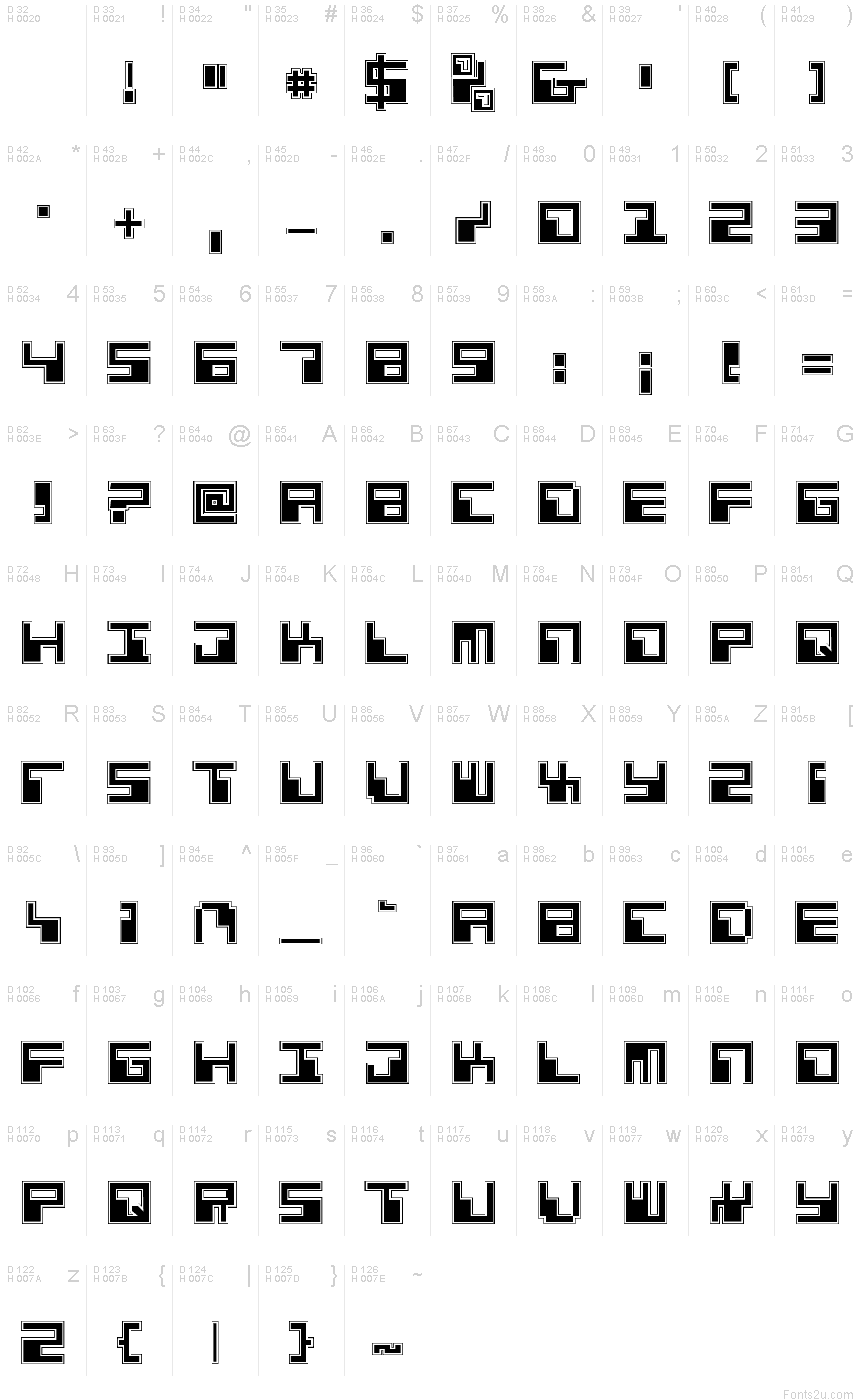
Phaser Bank Pro od Iconian Fonts to darmowy, futurystyczny font typu display w stylu techno, z szerokimi, kwadratowymi wielkimi literami i wyrazistą konstrukcją dwuliniową. Litery kojarzą się ze znakami sci-fi z automatów do gier lub paneli sterowania, z pudełkowymi kształtami zewnętrznymi, wpuszczanymi obrysami i prostymi kątami, które powtarzają się w całym kroju.
Naturalnie pasuje do logo gier, nagłówków plakatów, okładek albumów, plansz tytułowych i ulotek klubowych, gdzie krótkie słowa wymagają tego ostrego, elektronicznego klimatu. Jako darmowy font świetnie sprawdza się również w logotypach marek i monogramach, ponieważ warstwowy układ obrysów sprawia, że nawet kilka liter zyskuje wykończony, emblematyczny charakter.